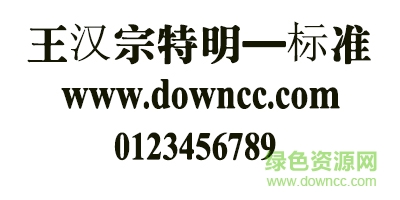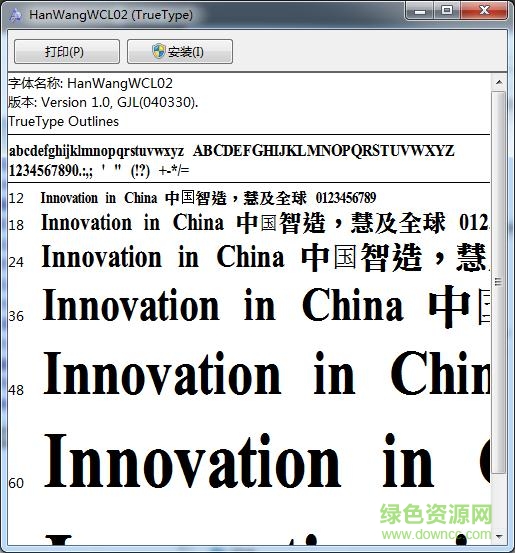
王漢宗特明體—標準字體在印刷、設計、排版行業(yè)使用的比較多。這個字體外形如同行云流水一樣富有朝氣和靈性!是同類字體中最受歡迎的明體字體!喜歡的用戶快來綠色資源網下載吧!
王漢宗特明體一標準是一款用于美工設計方面的字體,該字體遒勁豪放、布局精當、結構嚴謹,看上去十分美觀,可以廣泛應用于名片設計、新聞媒體、廣告設計、宣傳海報、ppt、影視制作以及內容用字等領域!
2.整體效果非常統(tǒng)一,且字庫完整。
3.字體流暢鏗鏘有力,使用便捷彰顯個性。